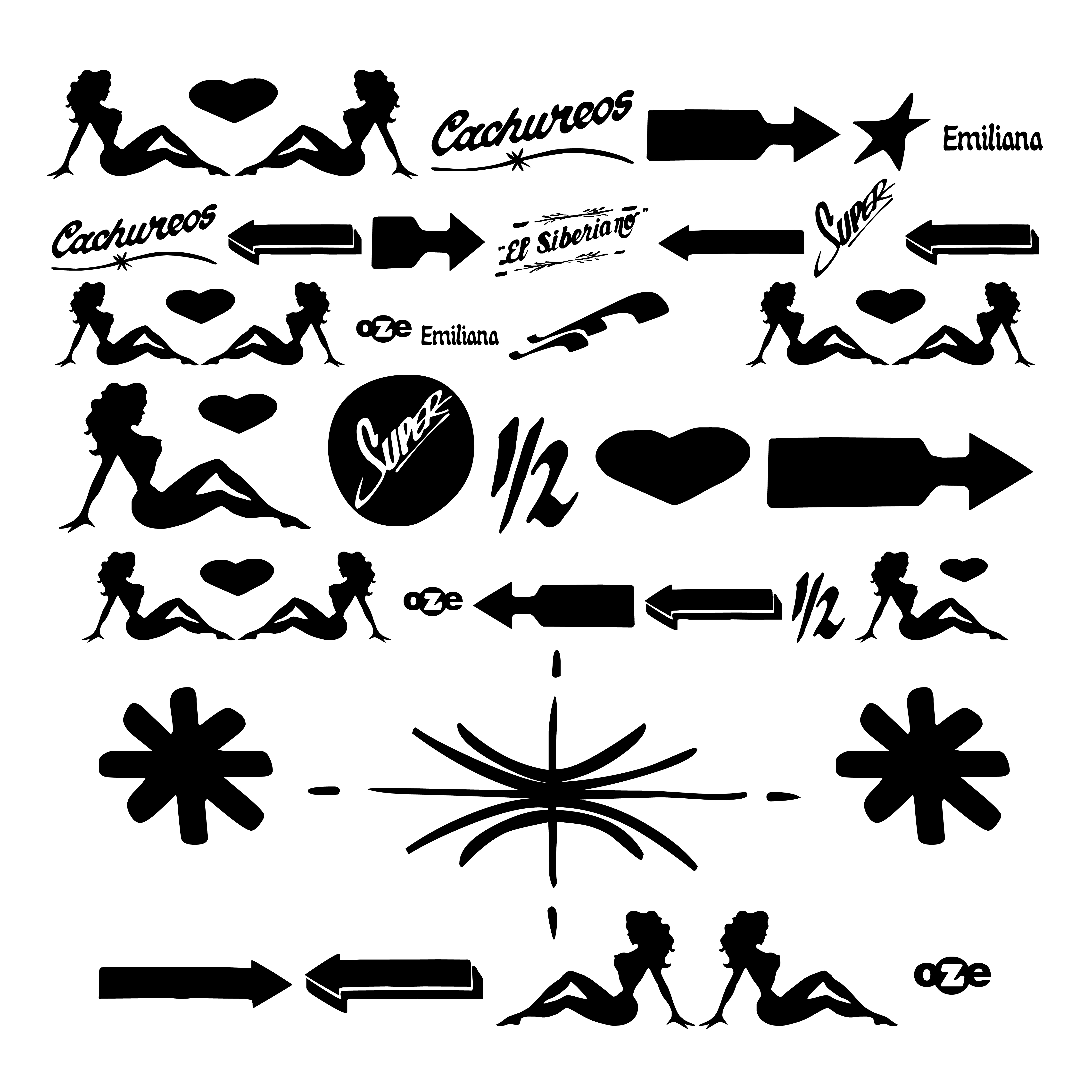
TCLhueaitas Regular
| Año | 1998 |
| Créditos | José Soto, Luis Antonio Rojas |
| Descripción | Rescate tipográfico de letrero urbano popular 1998, San Bernardo. Santiago. |
| Estudio | TUPs |